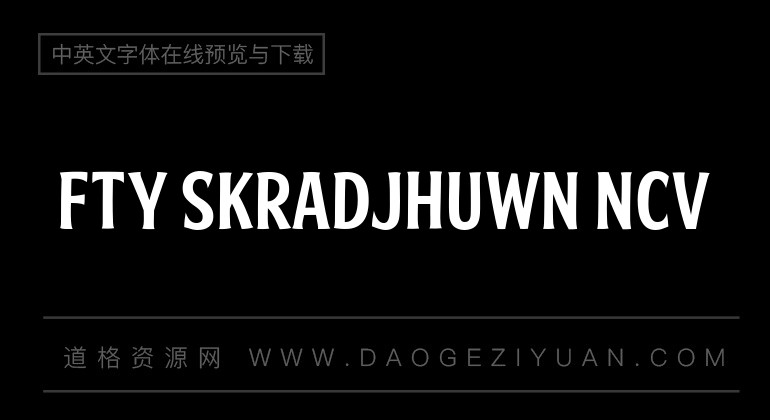
? FTY Skradjhuwn NCV是一款粗体字体,它有一种独特的英式风格,它的字形结构具有极强的视觉冲击力,具有突出的可读性,适合用于标题和报刊等。它具有鲜明的明暗对比,具有较强的视觉冲击力,可以让文字更加突出,更加显眼。内容介绍
FTY Skradjhuwn NCV是一款非常不错的手写艺术字体,具有很好的视觉感,适合于文化类的宣传设计、商业类品牌的广告和产品包装设计以及个性化文字排版等较多场景。